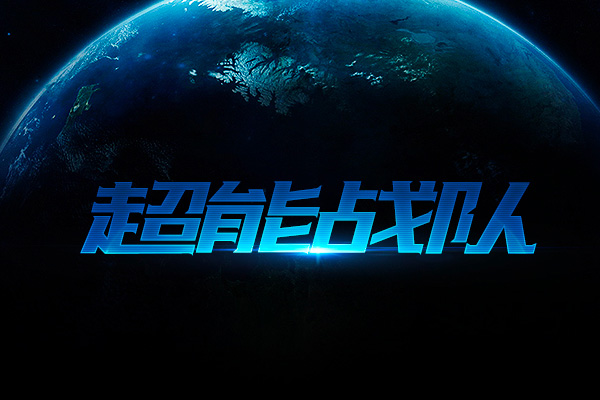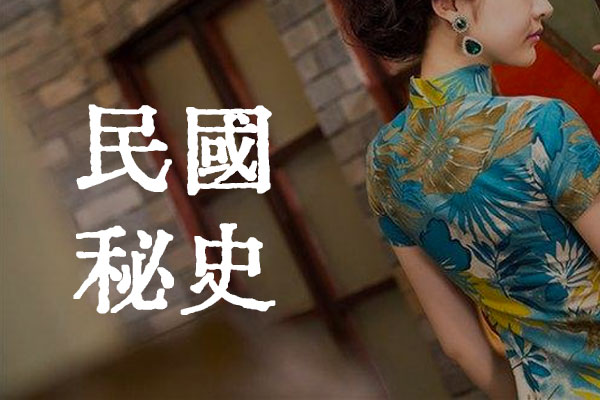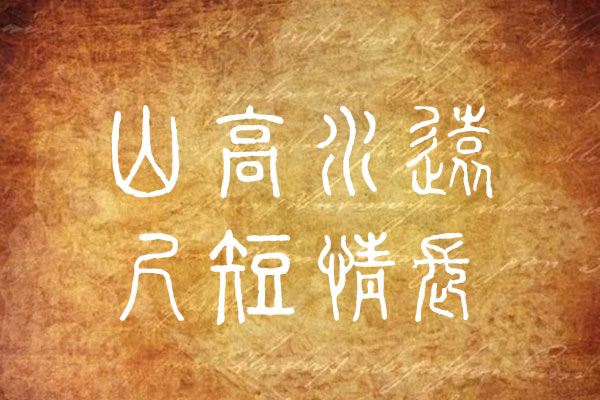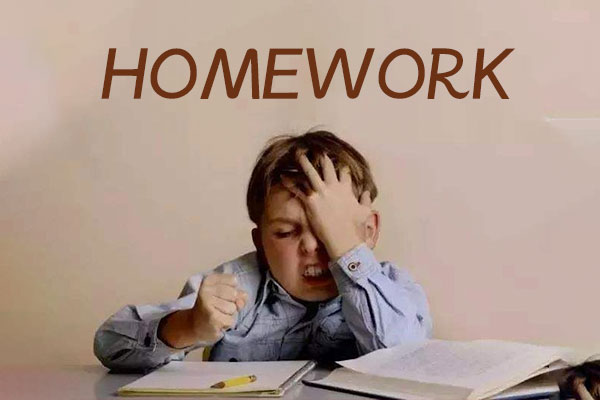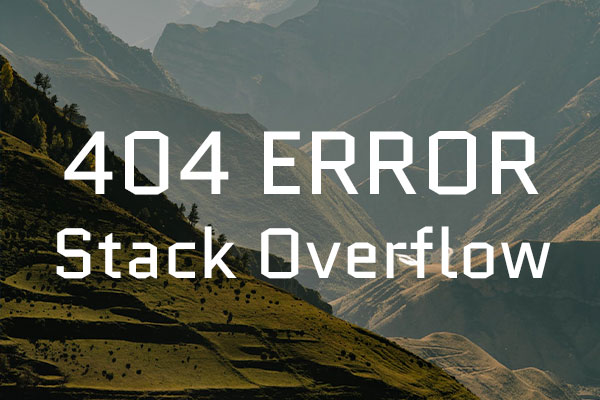
没那么难!6个简单实用的字体设计招式
在说字体设计之前我不得不提一下“格式塔心理学”,这是我们省略与变化字体笔画的理论基础。
我们的眼睛和大脑在观察事物、接收影像刺激的时候,会有一些特别的倾向。这些倾向常常可以帮助我们快速的辨别事物,有时候也会产生所谓的“错觉”。格式塔心理学重要的概念便是“整体不等于个体的总合”,举例来说:当我们在观察另一个人的时候,并不是先看到他的手、脚、头、眼睛、耳朵、鼻子,然后把这些视觉特征组合成一个称为“人”的组合。我们是直接的观察到人这个“整体”,而不是其他器官的“个体的总合”。格式塔心理学主要有相似性原理、连续性原理、封闭性原理、对称性原理等,举例来说,比如我们看到下面两组图形:
我们可以观察发现,虽然上图中的几组图形线条没有完全闭合,但是我们依然能看出它们是方形、圆、三角形,我们的大脑会自动填补元素与元素间的空白部分,形成一段不存在的图形,这就是格式塔心理学中所说的封闭性原理。这里弥补的元素就是线段和圆点,从而有助于我们得出一个“All roads lead to Rome.”这样的结论(善于举一反三,发现新的元素)。通俗地说格式塔就是感觉(知觉)的最终结果。是我们在心不在焉与没有引入反思的现象学状态时的感觉,这种感觉是不受外界因素约束的,来源于我们自己的感知。
现在字体设计都是用计算机辅助来做了,人就越来越懒,不愿意动手,很多设计师的电脑里都安装了上百款中文字体和上千款英文字体,(说的夸张,但是不为过)琳琅满目,感觉好像没什么必要去自己动手设计。其实不然,电脑字体库的字也是被设计出来的,有些字体还广泛运用于各行各业,如:黑体、宋体大多数运用在比较正规的文件上。Pingfang SC,Helvetica字体被很多互联网设计师用在了App界面设计中,成为了扁平化设计里面的信息承接元素。然而很多大公司都已经为公司的App设计了独特的字体(主要表现在0-9数字和A-Z字母上)。
设计师们都应该明白一件事情(物以稀为贵),做出具有自己个人风格的设计是最有意义,最有特色的,最能体现自己的设计价值。曾经有一位同事,深耕高端化妆品行业十几年,每个case设计都是那么的符合品牌风格(高端、大气、上档次),不过后来有一次做了一个公司邀请函类似的设计,上面涉及到几个字的字体设计,那真的叫一个丑(小伙伴都惊呆了,这是你设计的么,你认真了么),难道此时要说这位同事设计水平很差吗,不尽如此,她只是没服务过这样的设计,不擅长。一般情况下,国际高端品牌的设计都是不会出现字体设计的,它们更加崇尚极简主义,是用买了版权的字体,直接传达品牌的内涵(BMW、EsteeLauder,LouisVuittonden、Mercedes-benz等,有兴趣可以去看看)。那有人问了,这样不用做字体设计的设计还是设计么,肯定的回答,当然是了,而且是很牛的设计。(承载品牌文化的传播文案,富有意境的拍摄图片,配合文案的产品意境摄影等等,哪一项都考验着营销设计团队的点,有感觉的那个点,这里只可会意,不能言传)。写到这里,是不是有点跑题了,然而并没有。
做字体设计的前提:设计师必须要视所服务品牌的情况而定(不是所有的品牌都合适),服务品牌的品牌文化沉淀了多少年。一般情况下,没有做字体复杂设计的品牌都是有很多年的品牌传承,而且是走在了时尚的前沿(上面举了一些品牌)。像我们现在所处的互联网时代,很多品牌如雨后春笋般的涌现出来(品牌沉淀时间远不及很多实体品牌),需要通过一些变化多端的字体设计来迎合消费者(要求越来越高),从而衍生出很多风格差异化很大的设计传播方式(卖萌耍贱、吐槽恶趣味、马赛克……不胜枚举)。这些风格更多的表现在公司运营上( 活动、企业文化周边产品、微博大号、微信公众号……),有了差异化的设计方式也就同步伴随着产生了多元化的字体设计,多元化就需要涉及到多种方法和理论支持。
字体设计的精髓:精通结构,移花接木;组合外形,达到内涵。很多初会门径的设计师会感叹:哇,他这个字体设计的好牛啊、这个变化的好有趣、好卡哇伊啊……(一波夸张的表情脑洞飘过~~),怎么样在字体上移花接木,妆点它们,废话不多说了,直接看下面的几种方法(更加实用,比很多知识论坛里面的来的简单,粗暴,直接)
第一式:移花替换 妙手回春
移花替换是根据文字的内容意思,在统一形态的文字元素加入另类不同的图形元素或文字元素。用某一形象替代字体的某个部分或某一笔画,这些形象或写实或夸张。将文字的局部替换,是文字的内涵外露,在形象和感官上都增加了一定的艺术感染力。
第二式:移花共生 左右互搏
共生是文字图形化设计中广泛运用的形式。文字是一种视觉图形,它们的线条有着强烈的构成性和关联性,可以从单纯的构成角度来看到文字与文字笔画之间的异同,寻找笔画之间的内在联系,找到他们可以共同利用的条件,把它们提取出来合并为一,运用到当前的字体设计中。
第三式:移花双仙 横细竖粗
双仙说的是文字里面的横和竖。选定好项目需要的字体后,把横笔画变成细长,竖笔画相对应加粗,让横与竖形成粗细鲜明对比,彰显设计风格。(为什么没有横粗竖细,大家可以自己尝试一下看看,向平衡度和识别度方面考虑一下,作者曾经因此被领导骂过,不提了,一个惨字了得)。
第四式:移花纷飞 藕断丝连
藕断丝连说的是字体设计中运用到的连笔。寻找一条适合需要设计的主题的公用笔画(创建笔画),制造字体间的连接,增强整体性。
第五式:移花如玉 炽热如火
炽热如火,一般指用在游戏里面的材质,构建最直接的笔画,结合字意,通感传达,精心打磨,细致深入,强带入强感染。
无上绝招:移花接木 信手拈来
这是一种比较随意的无上心法,到这个层次的字体设计师估计已经尽淫各种字体设计大法(不限于上面概述的这几种),独孤求败了。靠的是什么,是感觉,是对于行业与设计项目的那一种特有的感觉,很神秘,像一个久远的远古门派,带着一种神秘面纱。
写在最后的话:
字体设计的方法还有很多,移花接木只是其中之一(武侠告诉我们,天下武功到了一定境界,都会殊途同归)。想要真正成为高手,必须不断学习和开拓自己的眼界(总结为阅历与审美层次)。当自己学会了一种方法,必须进行反复训练(作者太笨,只能这么办),才能形成质的飞跃。有时候“眼高手低”并非坏事,取长补短,不断总结和思考,才是提高的关键。
重要性
做好字体设计,对于视觉设计师来讲是一件特别有益的事情,主要有益于下面几个方面:
1)面对市场运营活动的时候,主题的字体设计属于活动界面的窗口,做好了主题字体设计等于活跃了画面。
2)面对Banner类别的Graphic设计,主题的字体设计好坏直接会影响到画面的结构,甚至好坏。